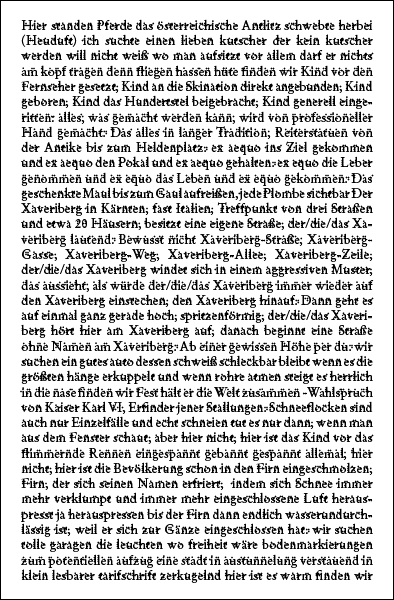
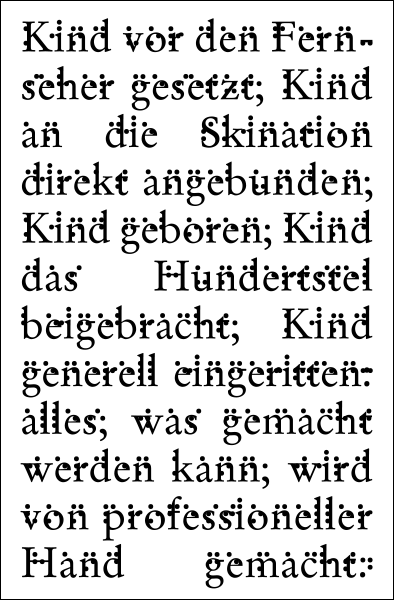
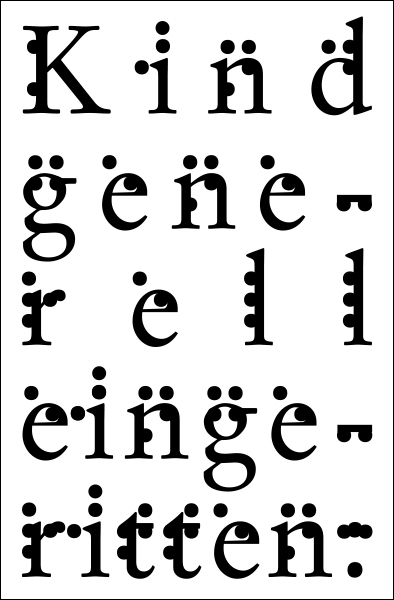
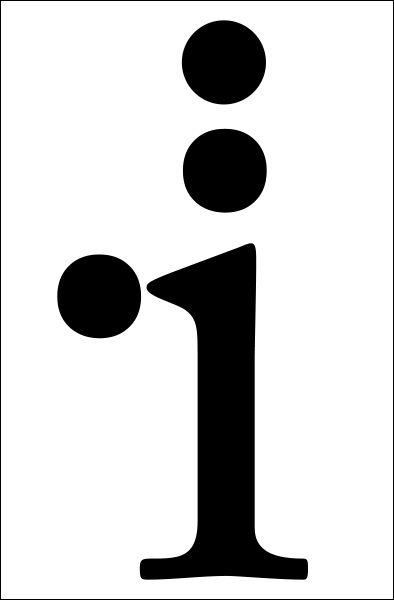
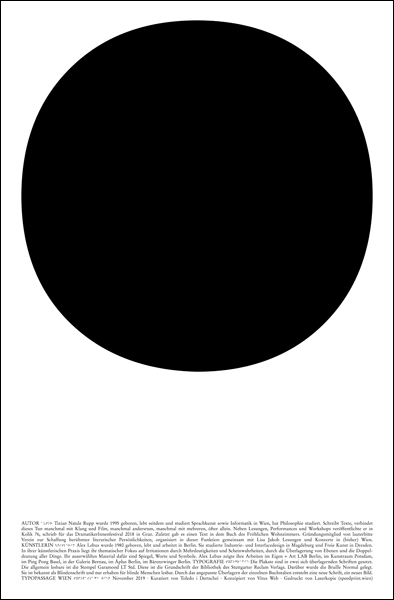
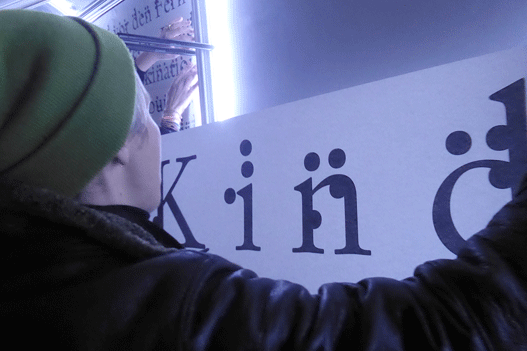
Text
Tizian Natale Rupp wurde 1995 geboren, lebt seitdem und studiert Sprachkunst sowie Informatik in Wien, hat Philosophie studiert. Schreibt Texte, verbindet dieses Tun manchmal mit Klang und Film, manchmal andersrum, manchmal mit mehreren, öfter allein. Neben Lesungen, Performances und Workshops veröffentlichte er in Kolik 76, schrieb für das DramatikerInnenfestival 2018 in Graz. Zuletzt gab es einen Text in dem Buch des Fröhlichen Wohnzimmers. Gründungsmitglied von lauterbitte – Verein zur Schaffung berühmter literarischer Persönlichkeiten –, organisiert in dieser Funktion gemeinsam mit Lisa Jakob Lesungen und Konzerte in (bisher) Wien.
Typografie
Die Plakate sind in zwei sich überlagernden Schriften gesetzt. Die allgemein lesbare ist die Stempel Garamond LT Std. Diese ist die Grundschrift der Bibliothek des Stuttgarter Reclam Verlags. Darüber wurde die Braille Normal gelegt. Sie ist bekannt als Blindenschrift und nur erhaben für blinde Menschen lesbar. Durch das angepasste Überlagern der einzelnen Buchstaben entsteht eine neue Schrift, ein neues Bild.
Gestaltung
Alex Lebus wurde 1980 geboren, lebt und arbeitet in Berlin. Sie studierte Industrie- und Interfacedesign in Magdeburg und Freie Kunst in Dresden. In ihrer künstlerischen Praxis liegt ihr thematischer Fokus auf Irritationen durch Mehrdeutigkeiten und Scheinwahrheiten, durch die Überlagerung von Ebenen und die Doppeldeutung aller Dinge. Ihr auserwähltes Material dafür sind Spiegel, Worte und Symbole. Alex Lebus zeigte ihre Arbeiten im Eigen + Art LAB Berlin, im Kunstraum Potsdam, im Ping Pong Basel, in der Galerie Bernau, im Åplus Berlin, im Bärenzwinger Berlin.